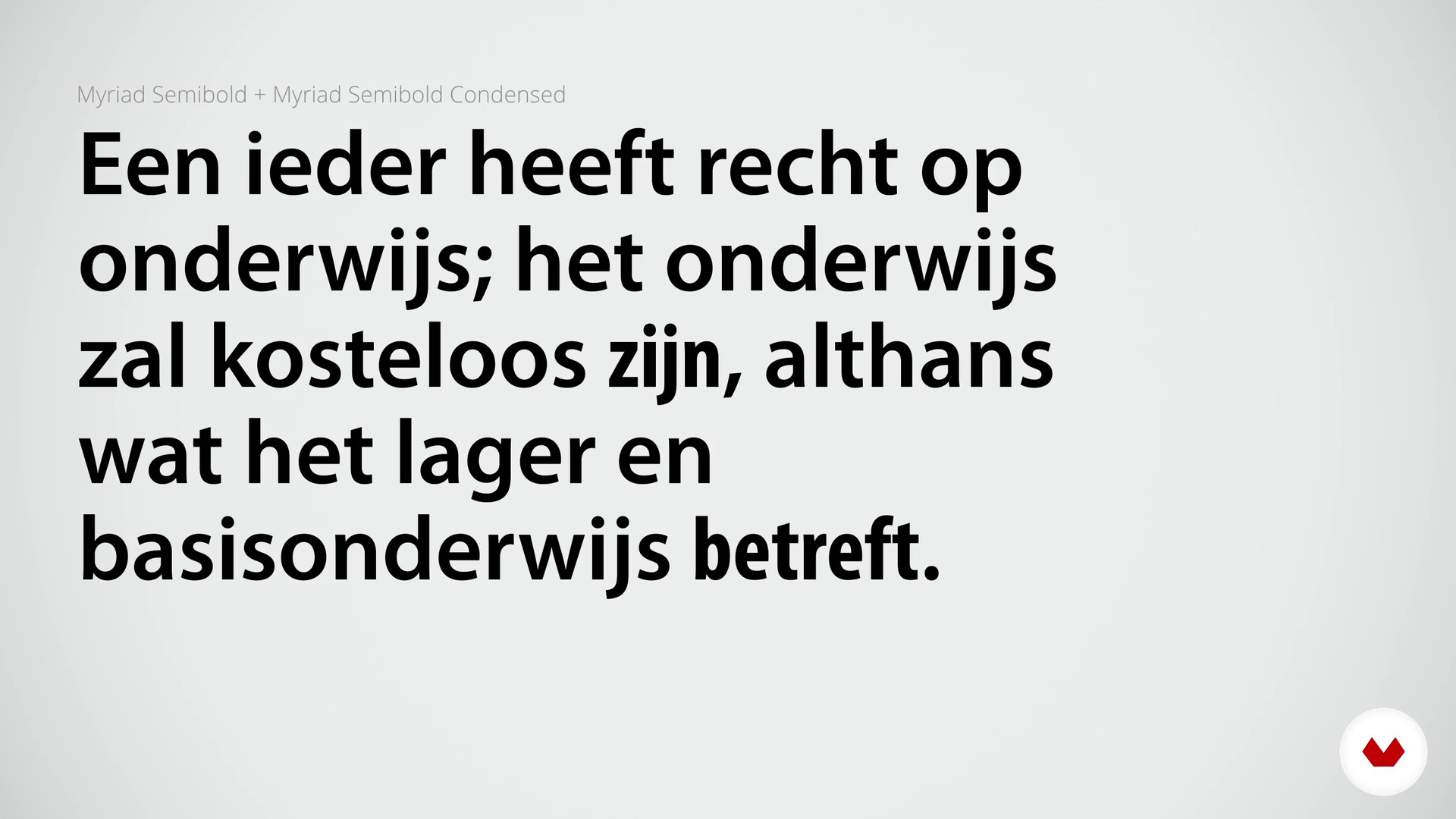
Combinar tipos
Sobre la videolección: Combinar tipos
Resumen
“Combinar tipografías es algo que a veces se puede convertir en un problema. En esta lección te doy algunos trucos para que esto no ocurra.”
En esta videolección, Enric Jardí aborda el tema: Combinar tipos, que forma parte del curso online de Domestika: Cómo elegir tipografías. Descubre qué cuenta cada tipo de letra y cómo escogerlas para tus trabajos.
Transcripción parcial del vídeo
“Combinar tipos En muchos de los trabajos, diría que la mayoría, deberás trabajar con más de una tipografía. Con lo cual, te enfrentarás al problema de cómo combinar estas dos letras. No solo cómo las escogemos, con qué criterio, sino qué trucos o qué cosas podemos hacerles a las letras para que combinen mejor. Cuando hablamos de utilizar distintos tipos de letras para distintas categorías, hablábamos normalmente de lo que hacíamos en conjuntos más complejos, como trabajos editoriales, en los cuales necesitábamos letras para titulares y letras para cuerpo de texto. Combinar distintas letras ...”